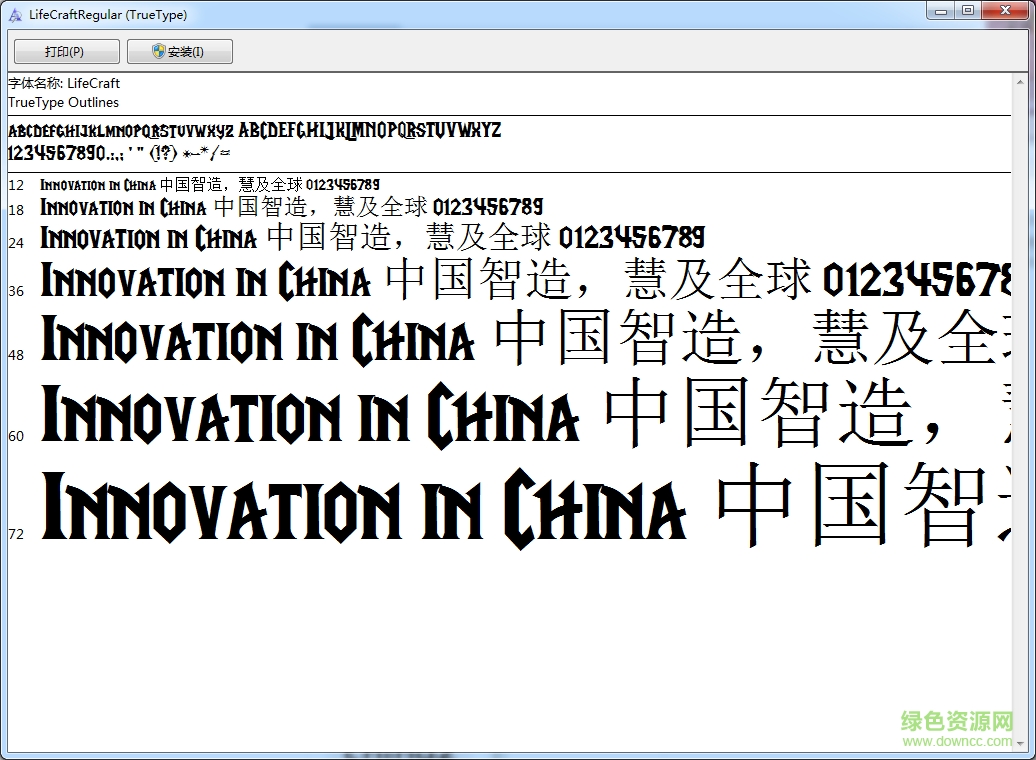
lifecraft字體是一款非常有個(gè)性的電腦字體,字體線條分明,支持漢字英文數(shù)字等多種方法輸入顯示,使用簡(jiǎn)單可直接導(dǎo)入ps中使用??靵砭G色資源網(wǎng)下載體驗(yàn)吧!
是一款十分不錯(cuò)的字體,在設(shè)計(jì)過程中經(jīng)常使用,能夠達(dá)到比較好的效果,在顯示的時(shí)候能夠十分顯眼